44款时尚英文窄体字体合集
窄体字体风格特点是在字形的宽度上进行压缩,使字体显得更加狭窄、细长。窄体字体常用于特定设计需求,如海报、标志、标题等,以在有限的空间内展现更多的文字内容。素材君为您整理了44款高品质的英文窄体字体,这些字体具有独特的视觉效果,既保持了字体的可读性,又呈现出一种独特的狭窄风格。
Herculine
这款字体拥有超紧凑和高耸的设计,是现代、简洁和时尚设计项目的不二之选。
AETHER
Nexusbold
Artyable Rassnam
Zuume
这款极具冲击力的浓缩显示字体系列,包含多种粗细和斜体,更拥有独特的 Zuume Cut 变体。全大写设计搭配醒目的凹口和延伸墨水陷阱,实用与美观兼具。Zuume Cut 系列更在平直的横笔中融入切片元素,赋予设计更强的动感。
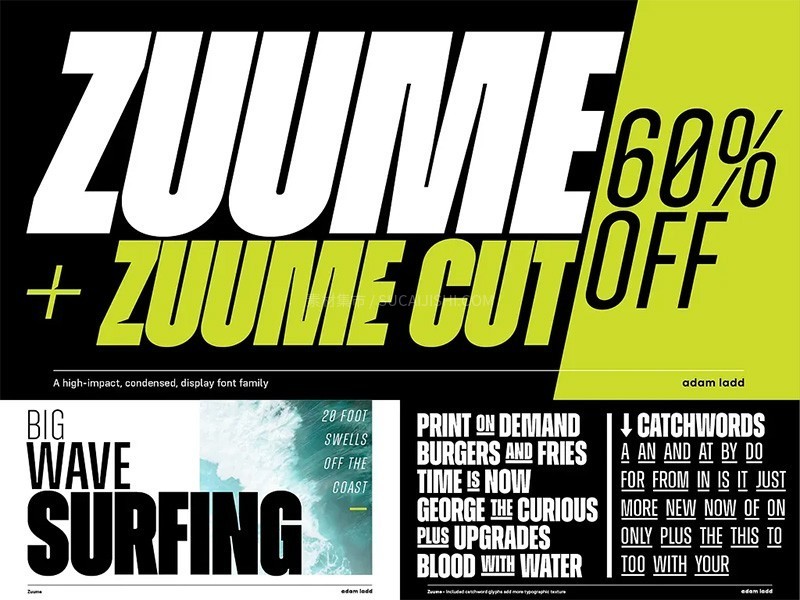
Zephyrus
一款极具现代未来感的窄体字体。其独特的浓缩方形造型,瞬间赋予您的设计前卫科技感。窄体的风格更显挺拔利落,是打造现代品牌标识、科技感网站以及未来主义风格设计的理想之选。
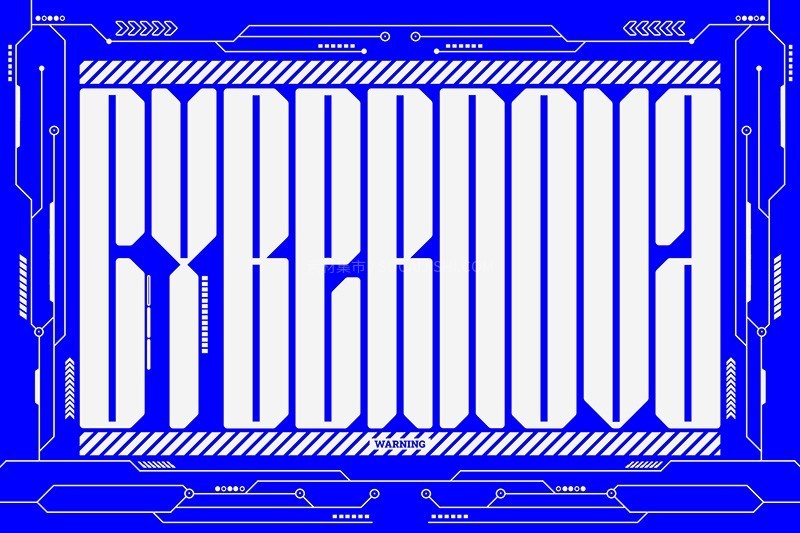
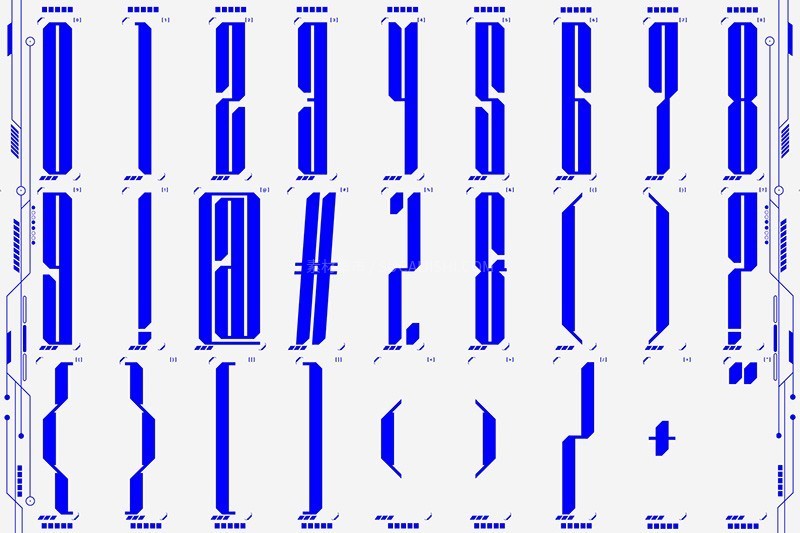
Vows Delierable
这款优雅的窄体衬线字体,以其独特的存在感,为您的设计注入精致气息。高挑而纤细的造型,在不喧宾夺主的情况下,巧妙地吸引目光。无论是品牌标识、时尚杂志,还是浪漫的婚礼请柬,Vows 都能以其独特的魅力,提升整体美感。
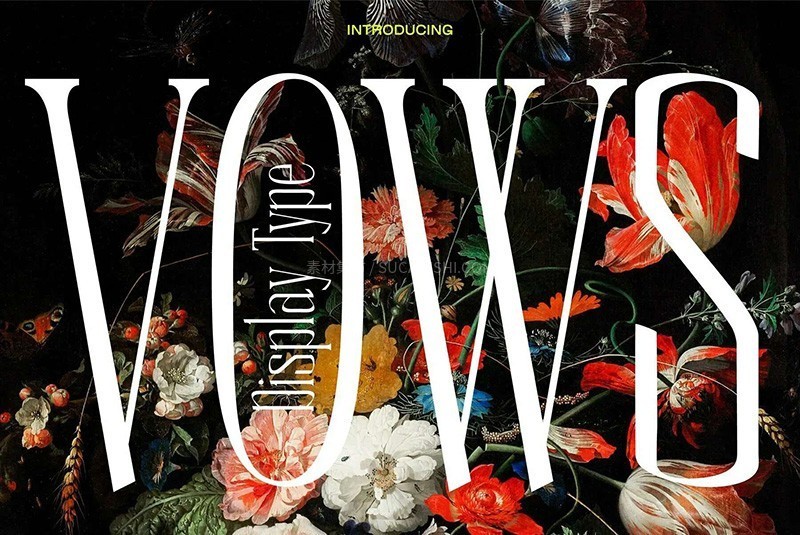
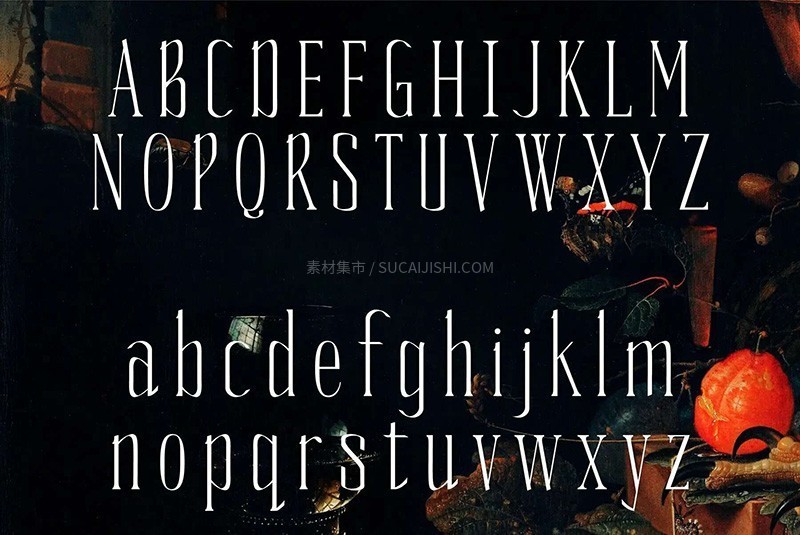
TT Frantz
TT Frantz 是一款复古衬线字体。这款字体具有独特的设计风格,融合了古典与现代的元素,适用于多种设计场景。
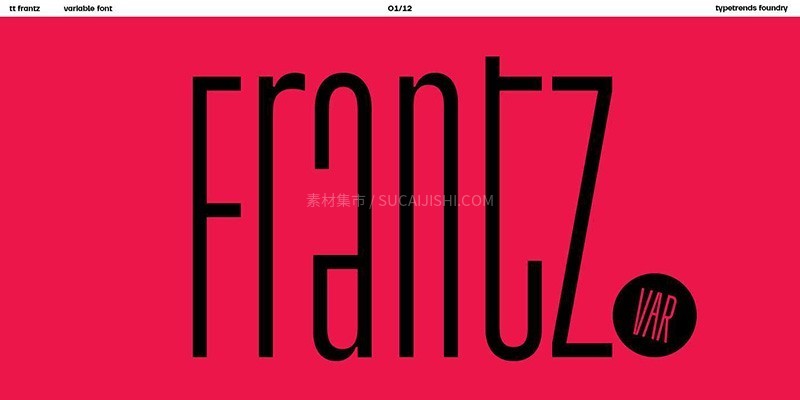
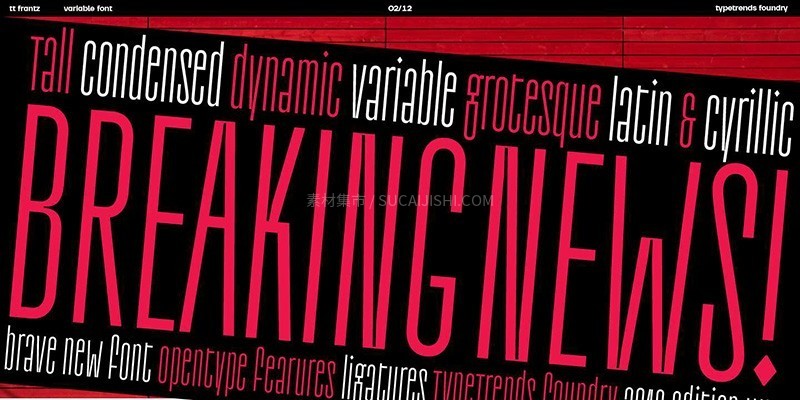
Synaptix
一款极具冲击力的窄体字,配有简约的字体和数字,拥有高而细长的形状,赋予了独特的超现代美感。
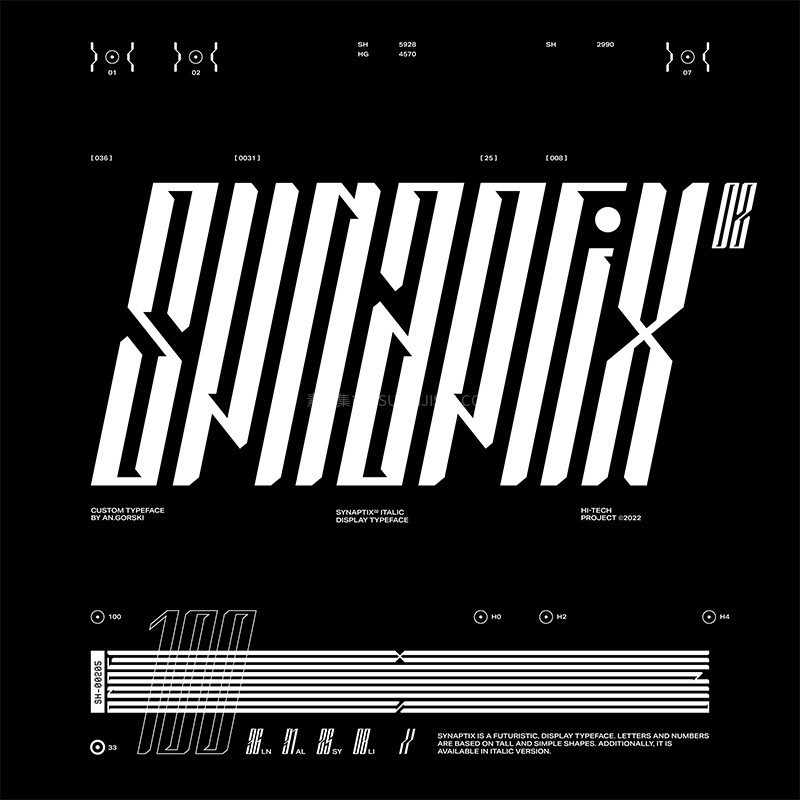
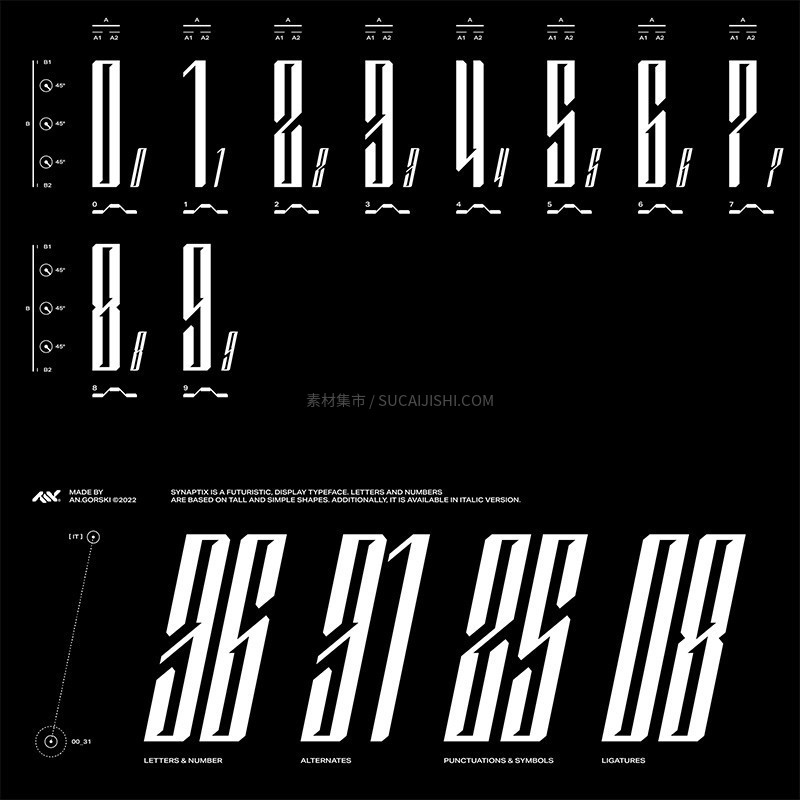
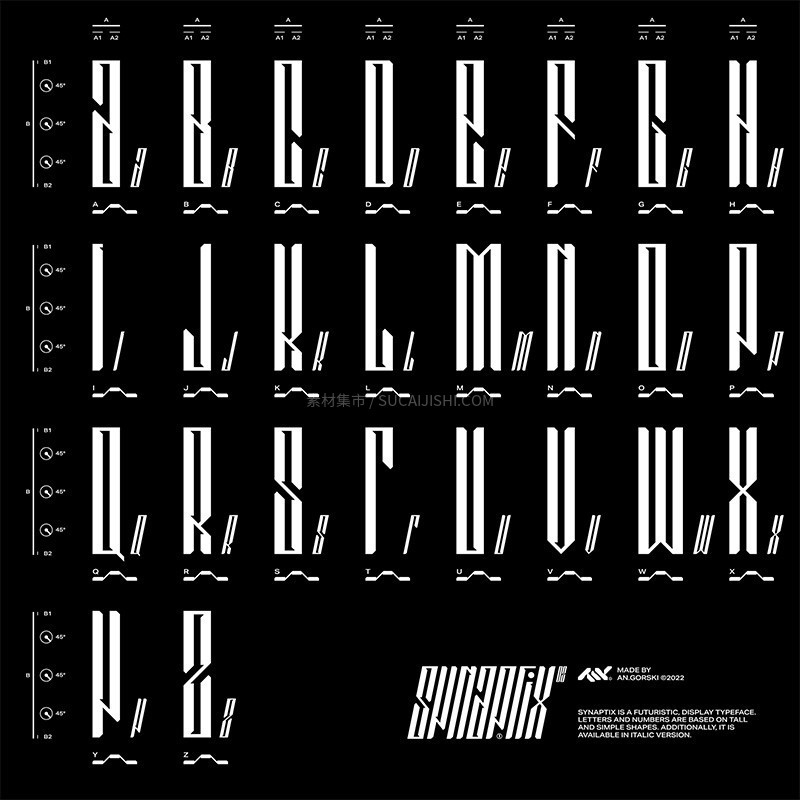
SUPR-Tall
一款功能性很强的英文字体,它的高度压缩和简洁风格使其在各种设计场景中都具有广泛的用途。
Smoosh
一款具有独特风格的字体,它结合了衬线字体的经典元素和窄字体的现代感。
SK Shpala
这款字体通过宽线条和纤细间隙的系统性组合,创造出令人难忘的字符图案。字体名称“Shpala”意指铁路枕木,完美地概括了其从上方俯视时如同铁轨般的视觉特征。
Agharti
Agharti Font
Amsterdam
Banigar
Bean
DazedandCondensed
dr-spindling-display
Fokus
Galgo Condensed
Hagia Pro
HCGleam
Heliuk Modern Condensed
HEX Franklin
HS Monsnow
Humane
Kaldi
Killviners
Kilograph
Kulokale
Lorida
Maildore
Manchester Condensed
Meuga
MTCrisiant
Neubahn
Norline
Nucliometer
outward
POPFINE
Seriguela
Sigana